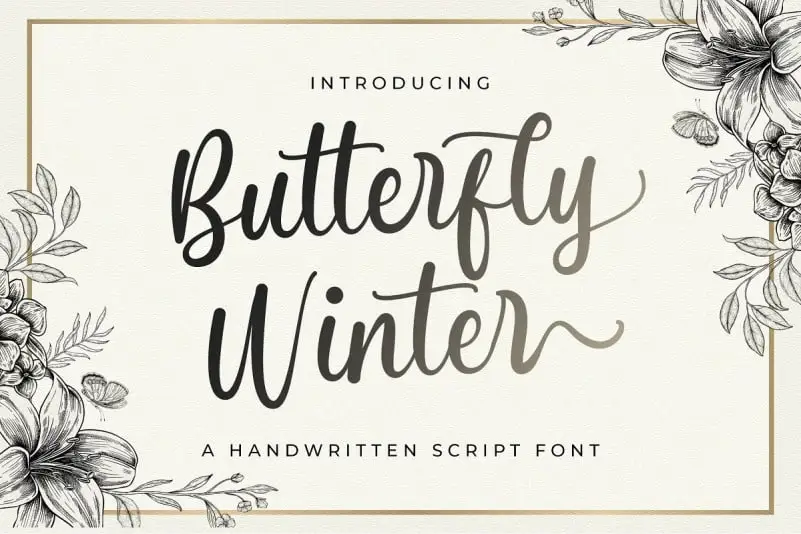
Butterfly Winter Script Font – Download Grátis
A Butterfly Winter Script Font é uma excelente escolha para quem busca uma fonte script que se destaca por sua originalidade. Desenvolvida pela StringLabs e lançada na 99designs, ela apresenta um traço arrebatador com uma característica distintiva no final da linha. Além disso, a Butterfly Winter Script traz caracteres belos e equilibrados, tornando-a perfeita para múltiplas aplicações gráficas. Através de sua beleza e equilíbrio, a fonte Butterfly Winter Script é versátil e se adapta bem a um amplo espectro de projetos criativos. Experimente adicioná-la aos seus próximos esboços ou ideias inovadoras para ver como ela pode transformar suas criações em algo verdadeiramente vívidos e impressionantes.